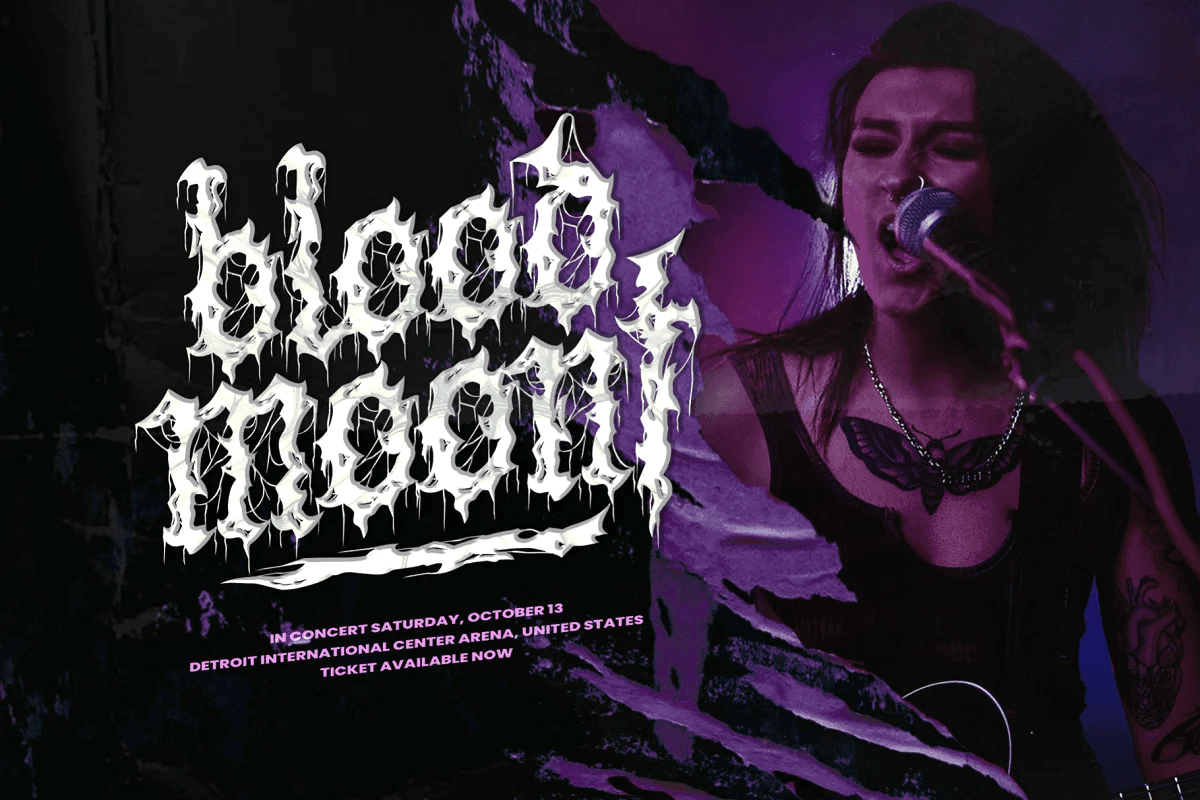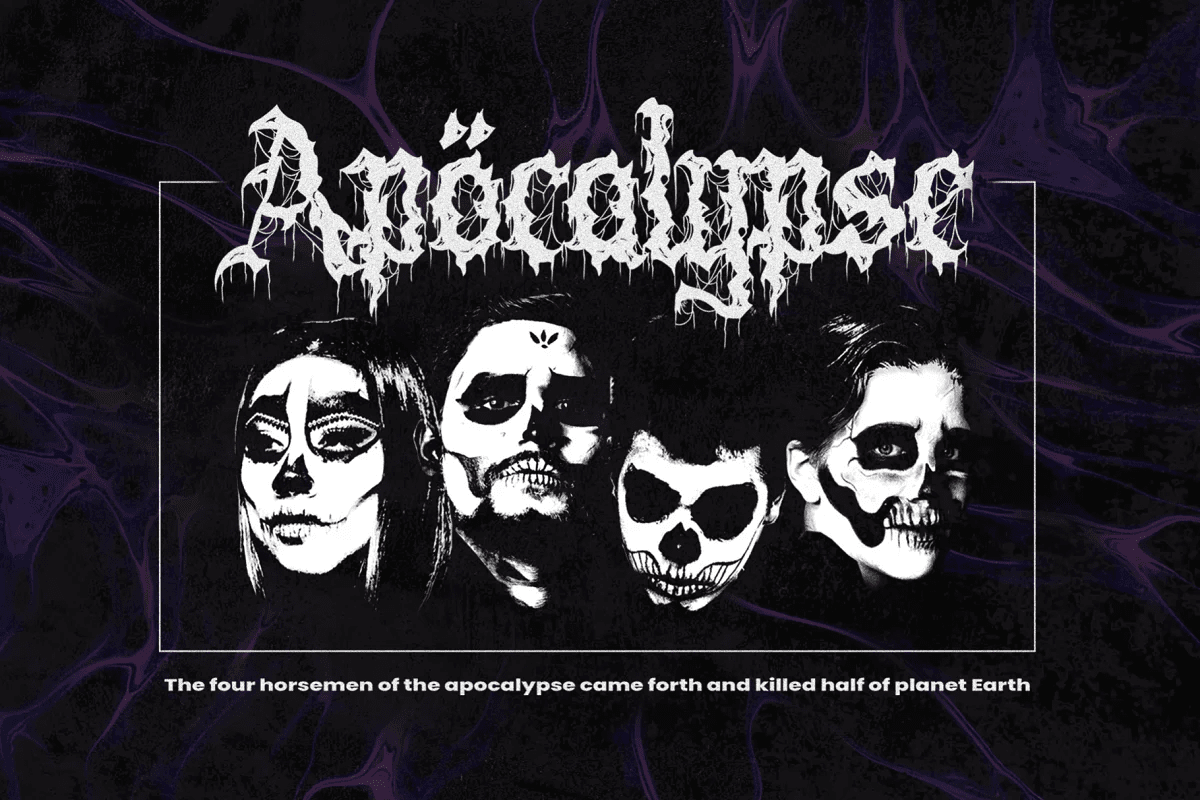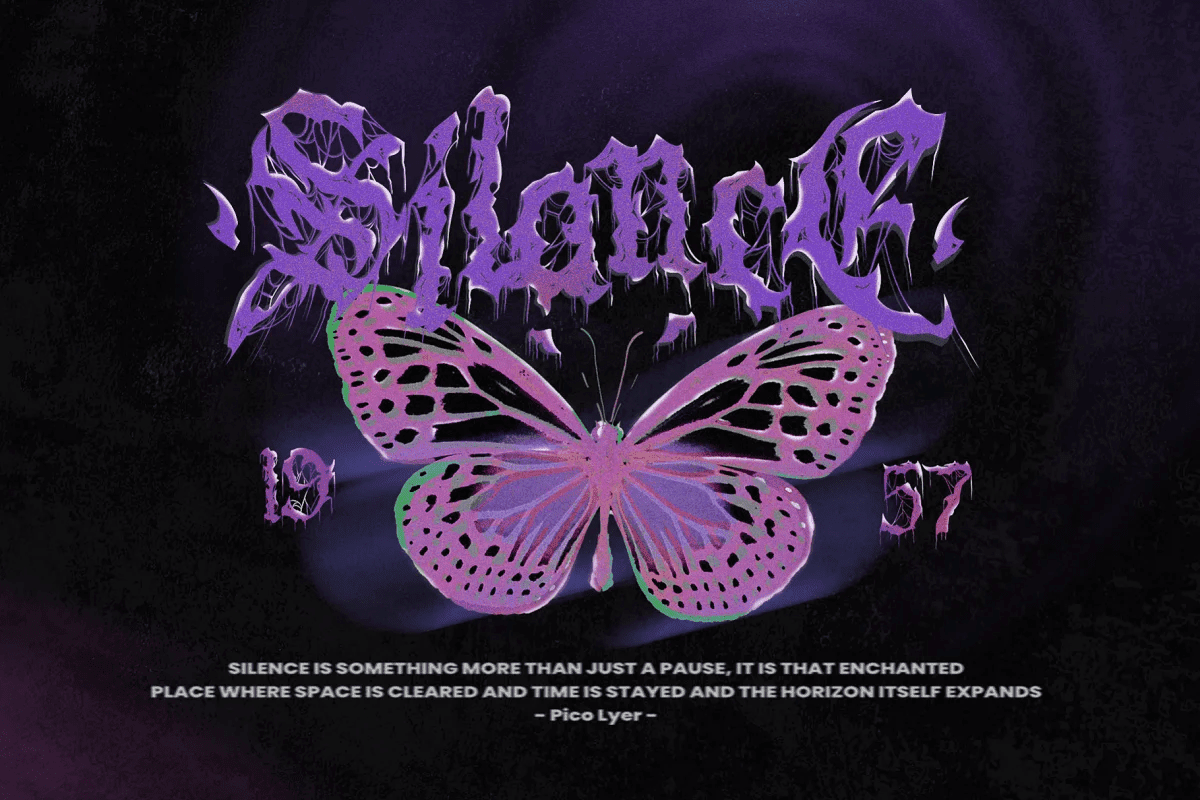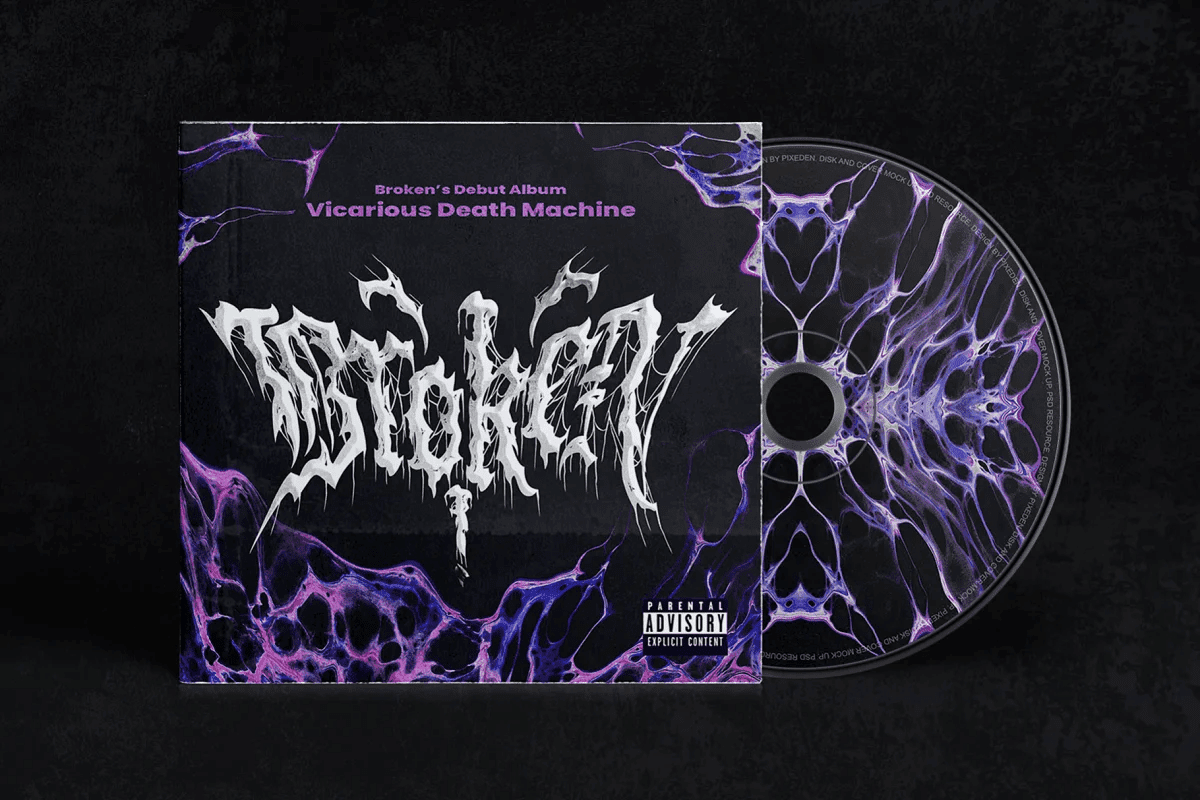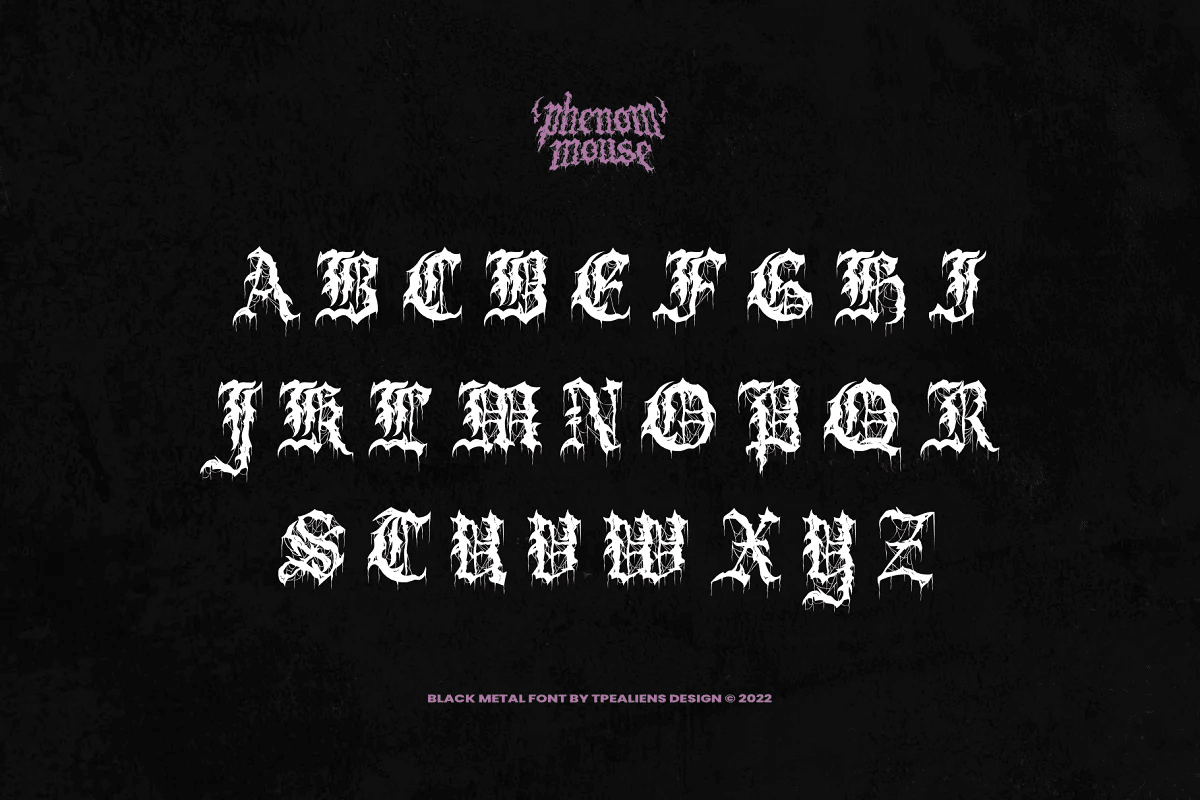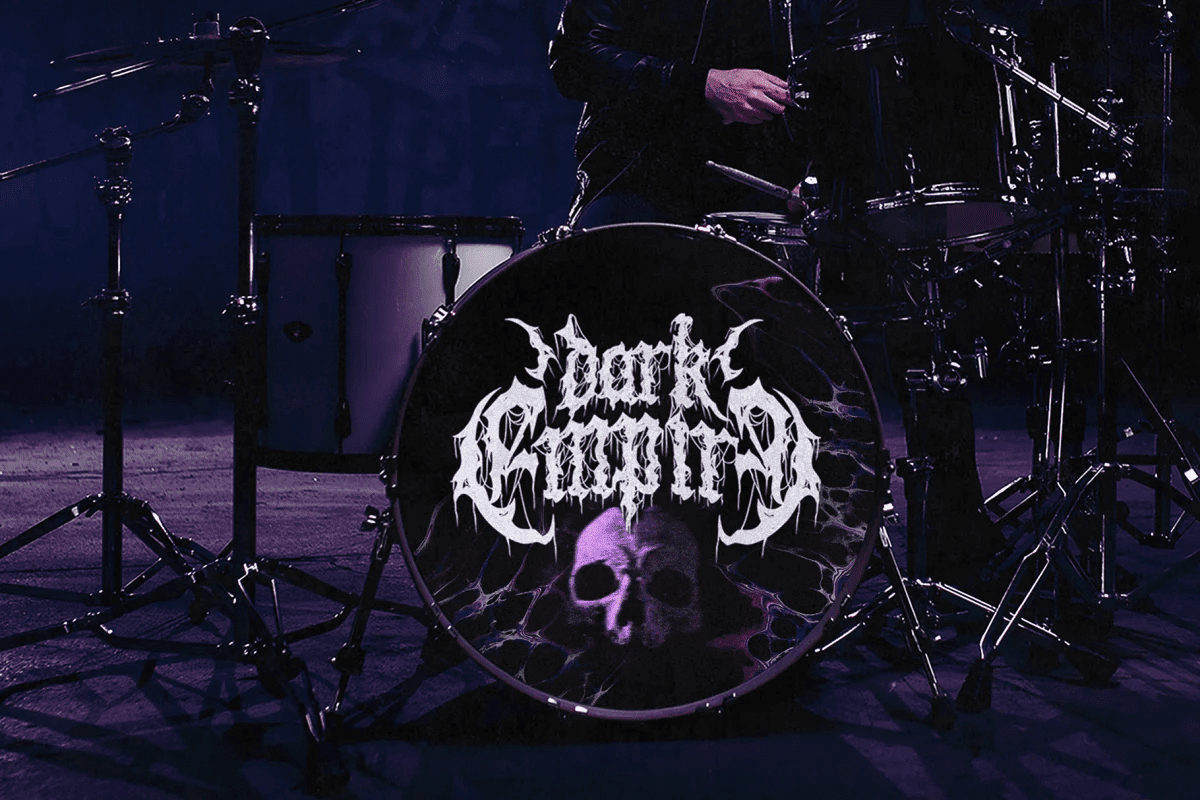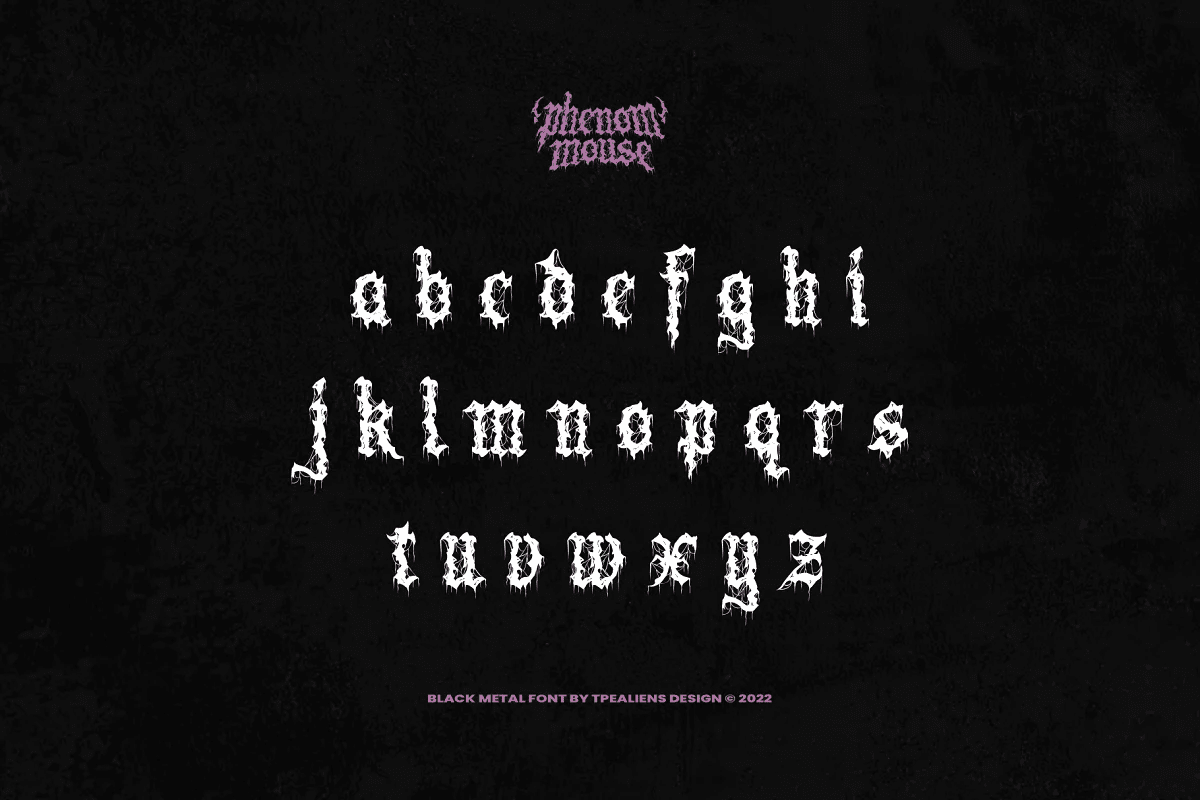
Phenom Mouse Font
Phenom Mouse là một phông chữ gothic được sửa đổi từ phông chữ blackletter, bằng cách thêm các bổ sung như “root” để tạo ra một phông chữ độc đáo thường được sử dụng cho logo ban nhạc metal, ban nhạc ngầm hoặc áp phích buổi hòa nhạc của ban nhạc. Phông chữ trông đáng sợ và phức tạp này không phù hợp cho một đoạn văn, vì thực chất nó chỉ là phông chữ hiển thị. Sự phát triển blackletter này có thể được phân loại thành các phông chữ hiện đại.